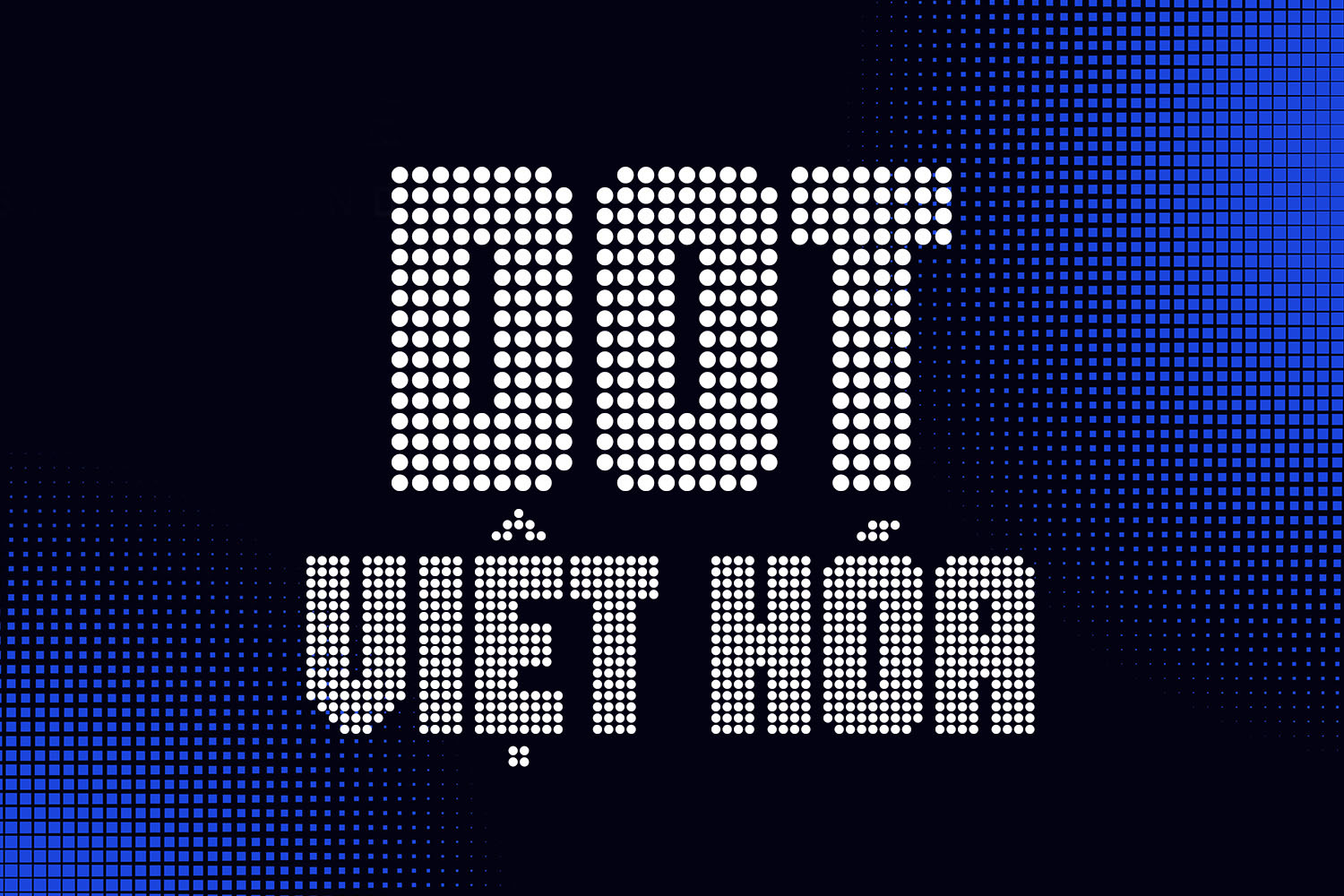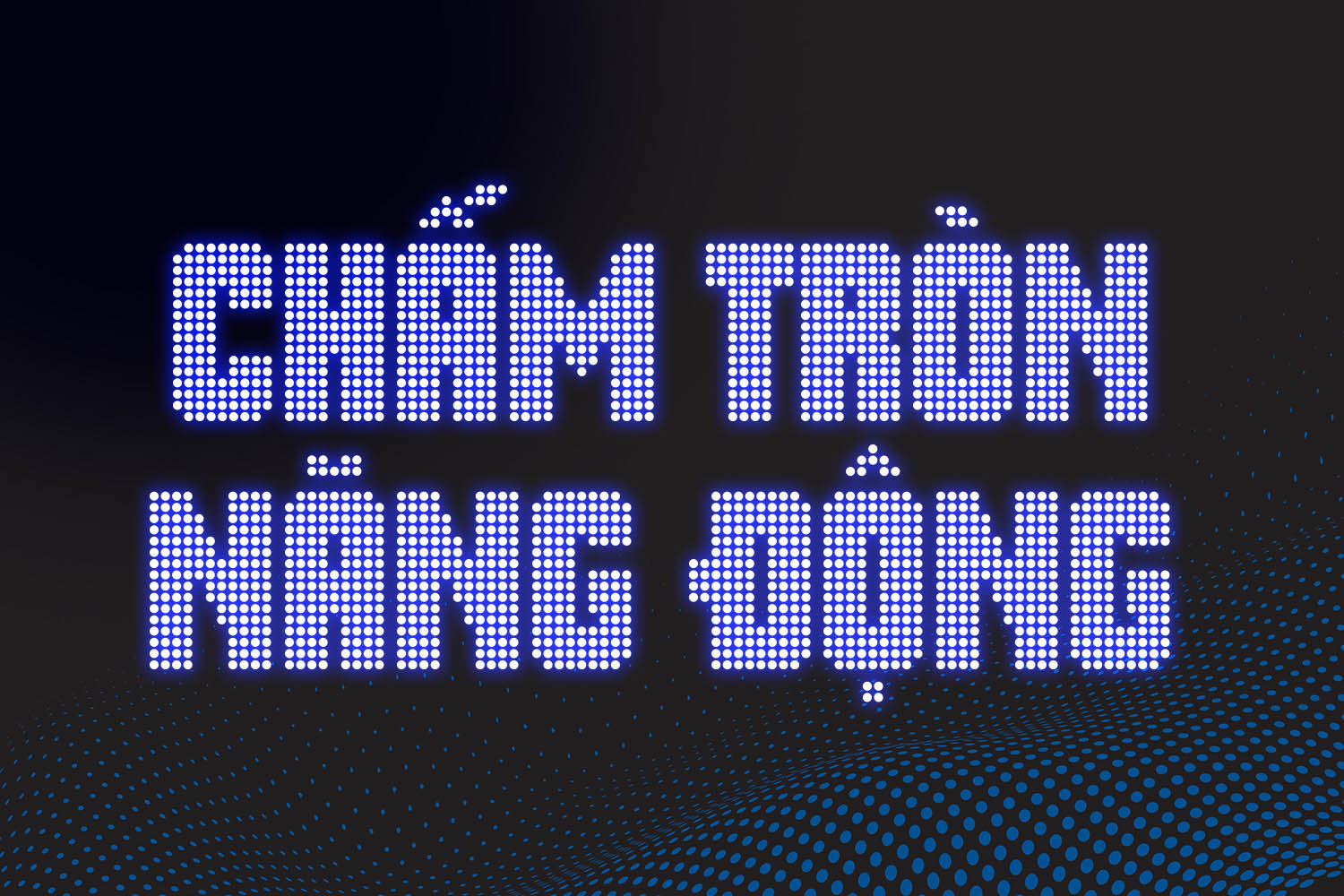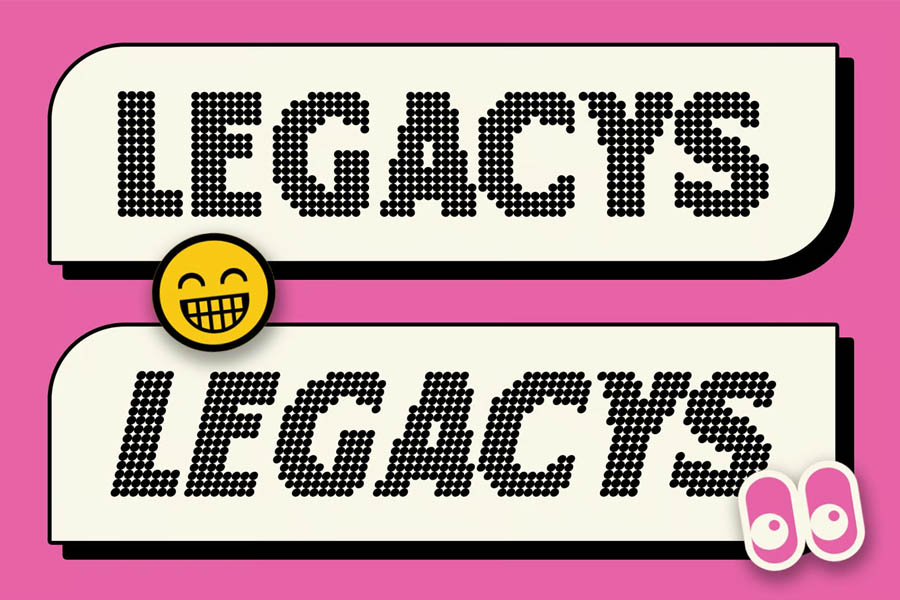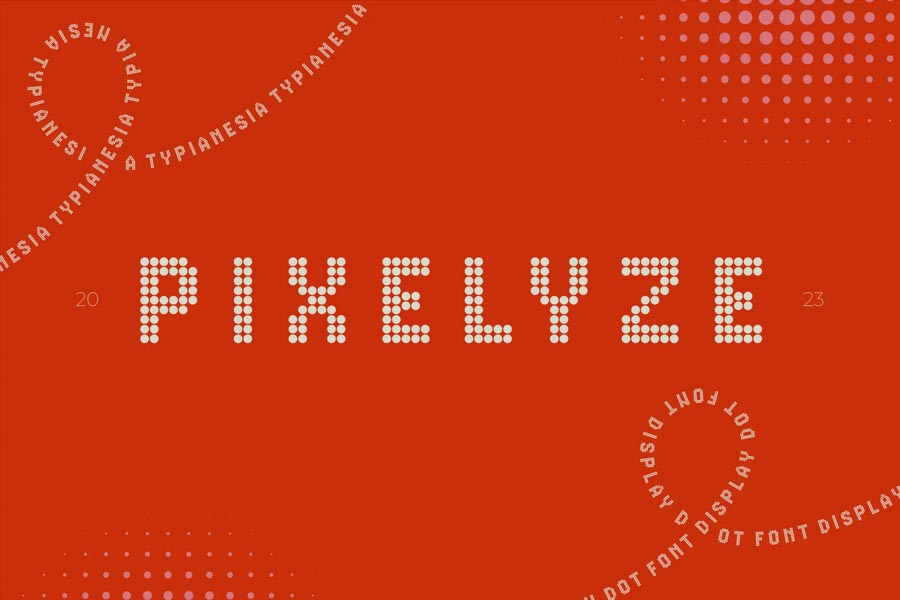
Font chữ chấm bi – Tổng hợp font chữ độc đáo, vui nhộn và sáng tạo
Font chữ chấm bi (thường được biết đến là dòng phông chữ Dotted, Polka Dot hoặc Matrix Font) là nhóm các phông chữ độc đáo được cấu thành từ vô số điểm chấm tròn li ti ghép lại theo khung hình học chữ cái. Với phong cách vừa vui nhộn, vừa gợi nhắc đến những bảng đèn LED rạp hát cổ điển và các trang vở tập tô chữ cho học sinh, phông chữ này là lựa chọn tuyệt vời cho các thiết kế bao bì bánh kẹo, đồ chơi trẻ em, thẻ học thông minh và ấn phẩm sự kiện sáng tạo. Doozypack.vn cung cấp link tải Font chữ chấm bi chuẩn kỹ thuật, giúp bạn sở hữu trọn bộ phông chữ độc lạ này mà không lo gặp bất kỳ lỗi hiển thị dấu tiếng Việt nào khi thiết kế in ấn.
Đặc điểm thẩm mỹ độc đáo của bộ font chữ chấm bi
Không đi theo sự liền mạch của các phông chữ thông thường, font chữ chấm bi tạo nên một ngôn ngữ thị giác đầy tính tương tác, biến từng ký tự thành một trò chơi ghép hình thú vị.
Mẫu chữ chấm bi độc đáo
Phong cách Dotted Typography ngộ nghĩnh và đầy tính tương tác
Đặc trưng lớn nhất của Font chữ chấm bi là các đường nét được tạo thành từ những hạt chấm tròn rời rạc nhưng được sắp đặt với khoảng cách vô cùng chuẩn xác. Cấu trúc này mang lại cảm giác nhẹ nhàng, thông thoáng và rất dễ thương, gợi liên tưởng đến những chiếc đầm chấm bi cổ điển hoặc các hạt kẹo đường ngọt ngào. Khi đặt phông chữ này làm tiêu đề trên bao bì, sản phẩm của bạn sẽ ngay lập tức lan tỏa năng lượng tích cực, kích thích sự tò mò và cảm giác thích thú của trẻ nhỏ cũng như giới trẻ.
Ứng dụng đa dạng từ giáo dục tiểu học đến nghệ thuật Retro
Phông chữ chấm bi sở hữu hai nhánh phong cách thị giác rõ rệt: dòng chữ nét chấm mộc mạc phục vụ trẻ em tập tô chữ cái (tracing font) và dòng chữ chấm bi bóng đèn (marquee bulb font) mang hơi thở rực rỡ của các rạp chiếu phim thế kỷ 20. Sự linh hoạt này giúp designer dễ dàng biến tấu từ những ấn phẩm giáo cụ mẫu mực đến các mẫu nhãn mác mang đậm chất Retro Pop-art.
Kiểu chữ trang trí nổi bật
Thiết kế typography sáng tạo